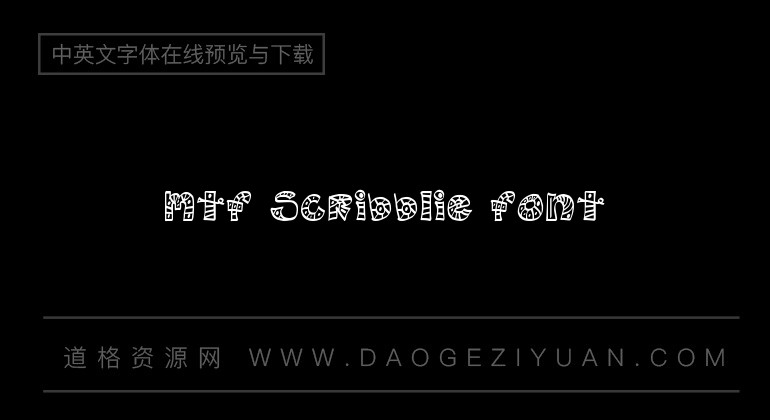
MTF Scribblie Font
MTF Scribblie Font是一种手写字体,它具有非常独特的风格和特点。这款字体的设计师是Amanda MTF,她的设计灵感来自于她的写作和涂鸦经验。该字体看起来像是在纸上随意涂鸦而成,非常适合用于艺术类的设计项目中。 MTF Scribblie Font包括大写字母、小写字母、数字和标点符号。它的字母形状不完美,有些字母看起来像是在急速涂鸦中草草完成,而有些字母则更加流畅和漂亮。这种不规则的形状和线条使得MTF Scribblie Font看起来非常生动和有趣。 MTF Scribblie Font很适合用于各种艺术和手工制品设计,比如海报、卡片、手册、T恤衫、包装设计等等。该字体充满了创造力和个性,可以让你的设计更加独特而有趣。
MTF Scribblie Font是一款非常不错的手写艺术字体,具有很好的视觉感,适合于文化类的宣传设计、商业类品牌的广告和产品包装设计以及个性化文字排版等较多场景。